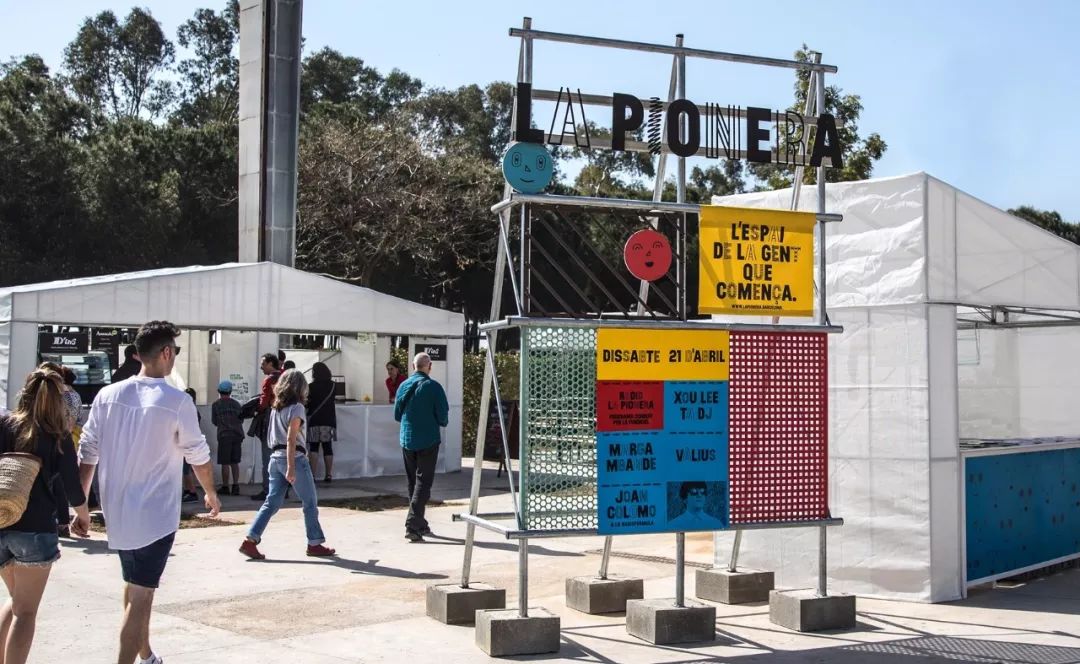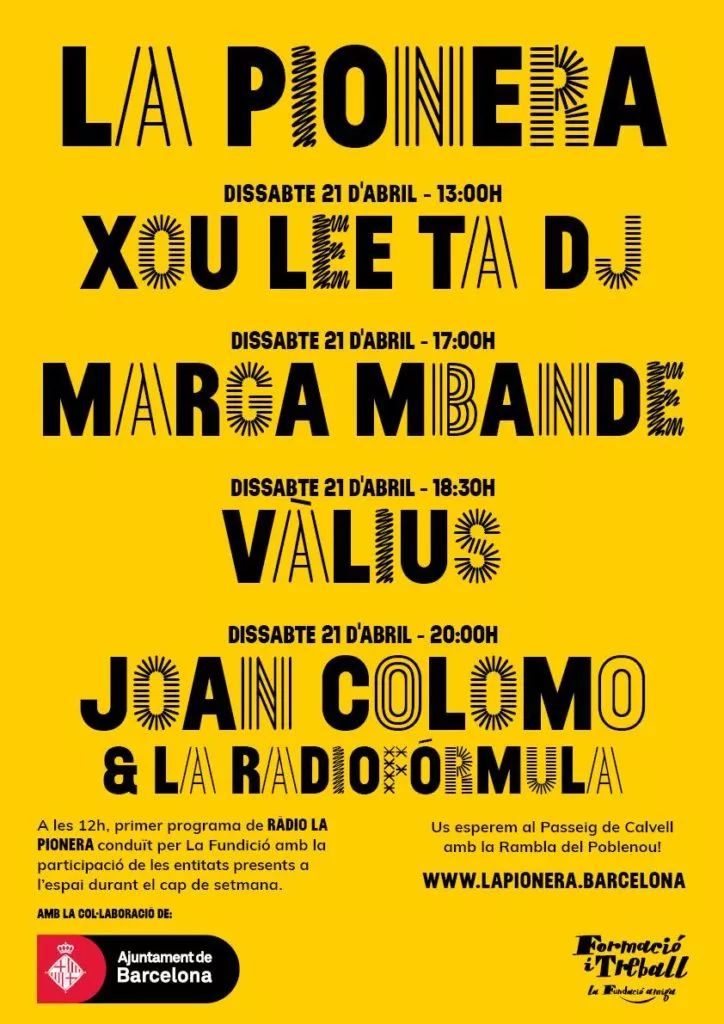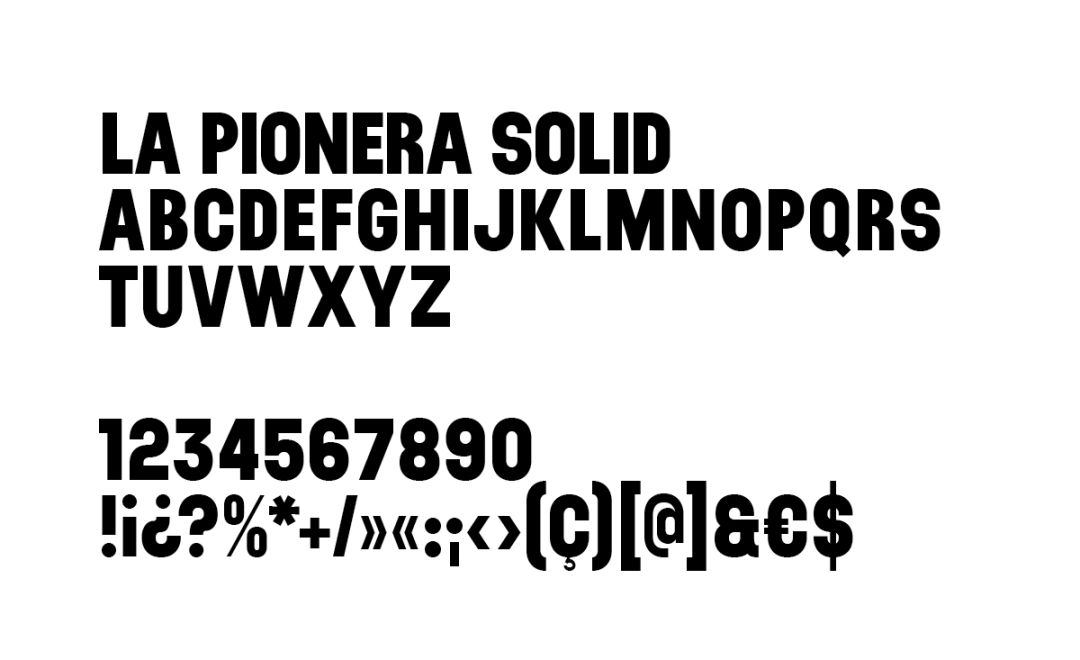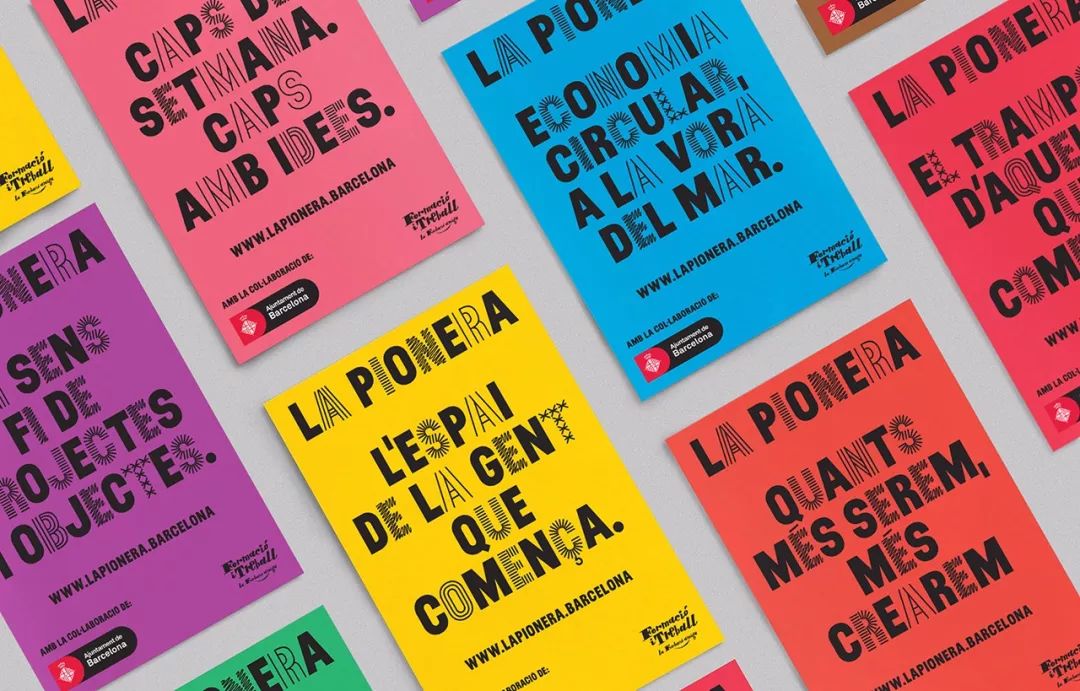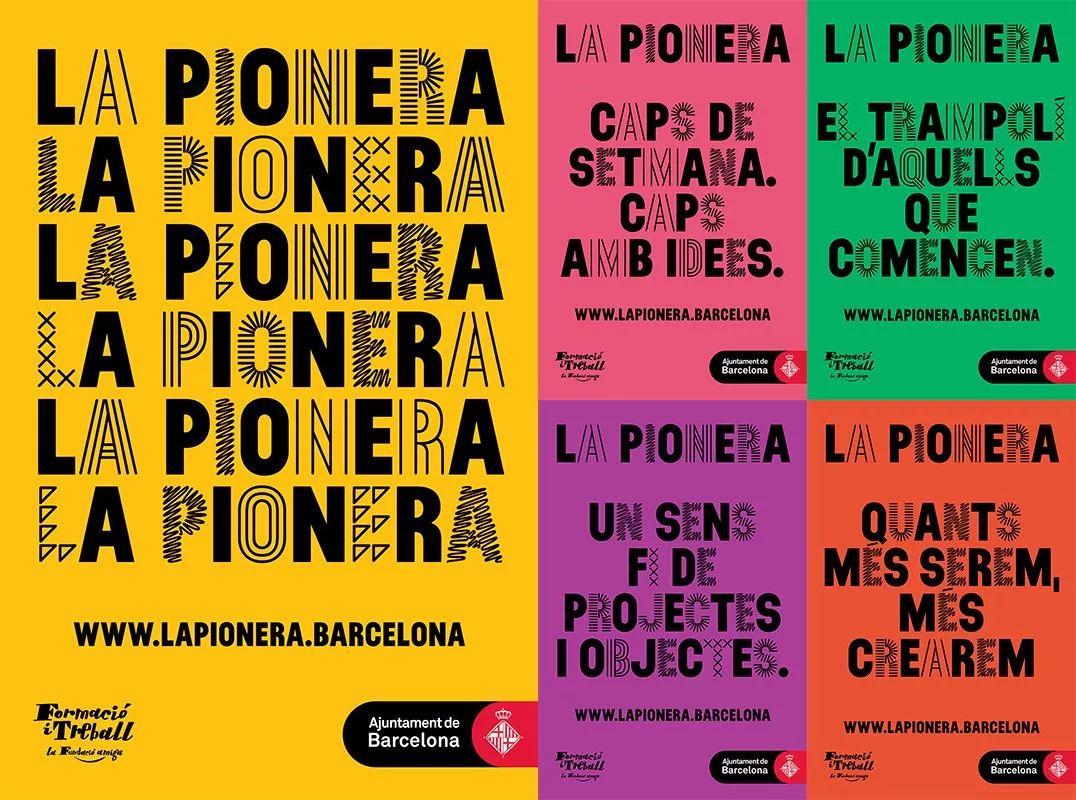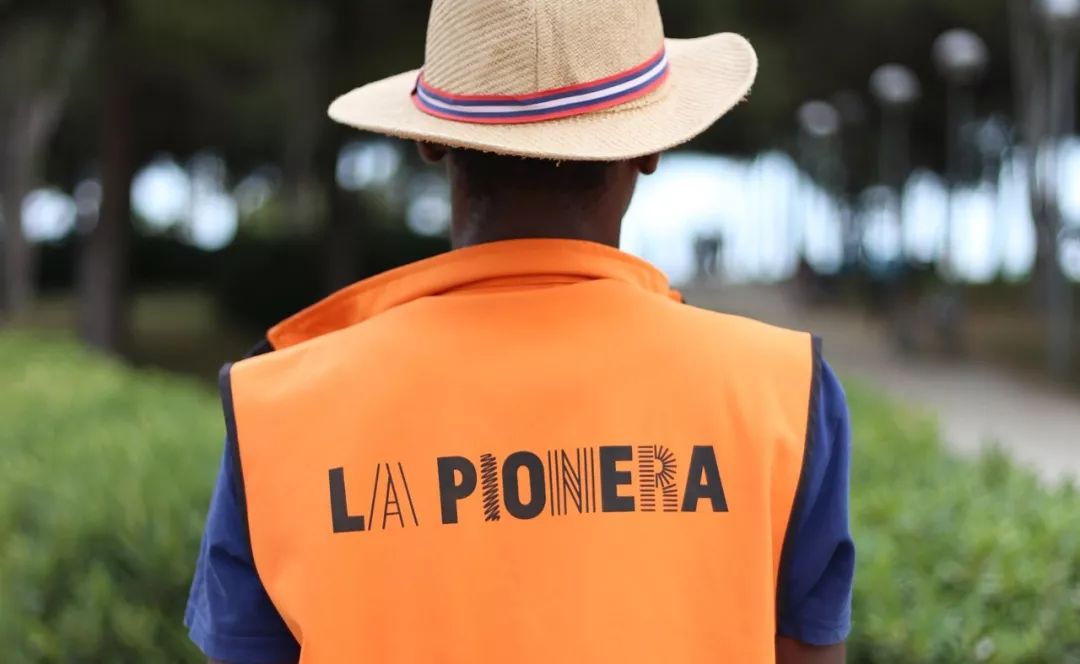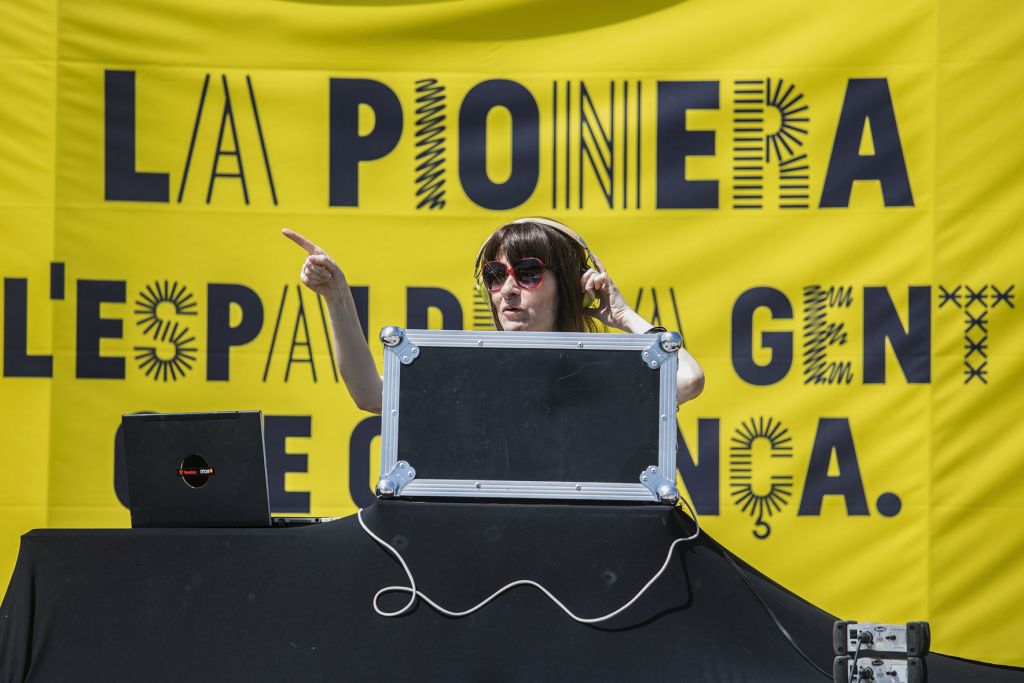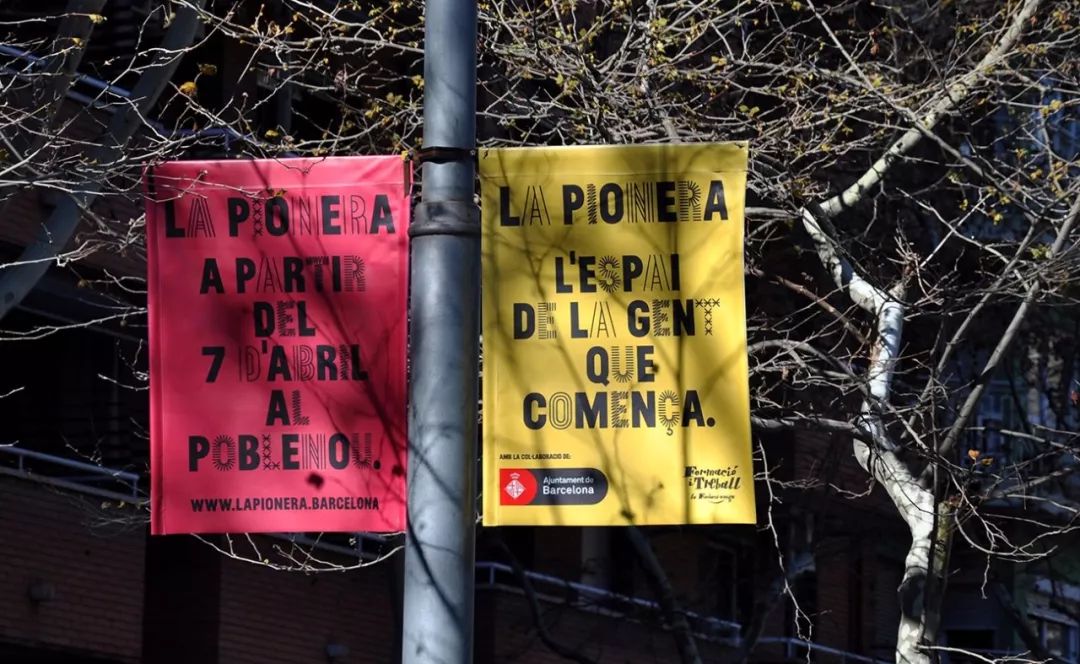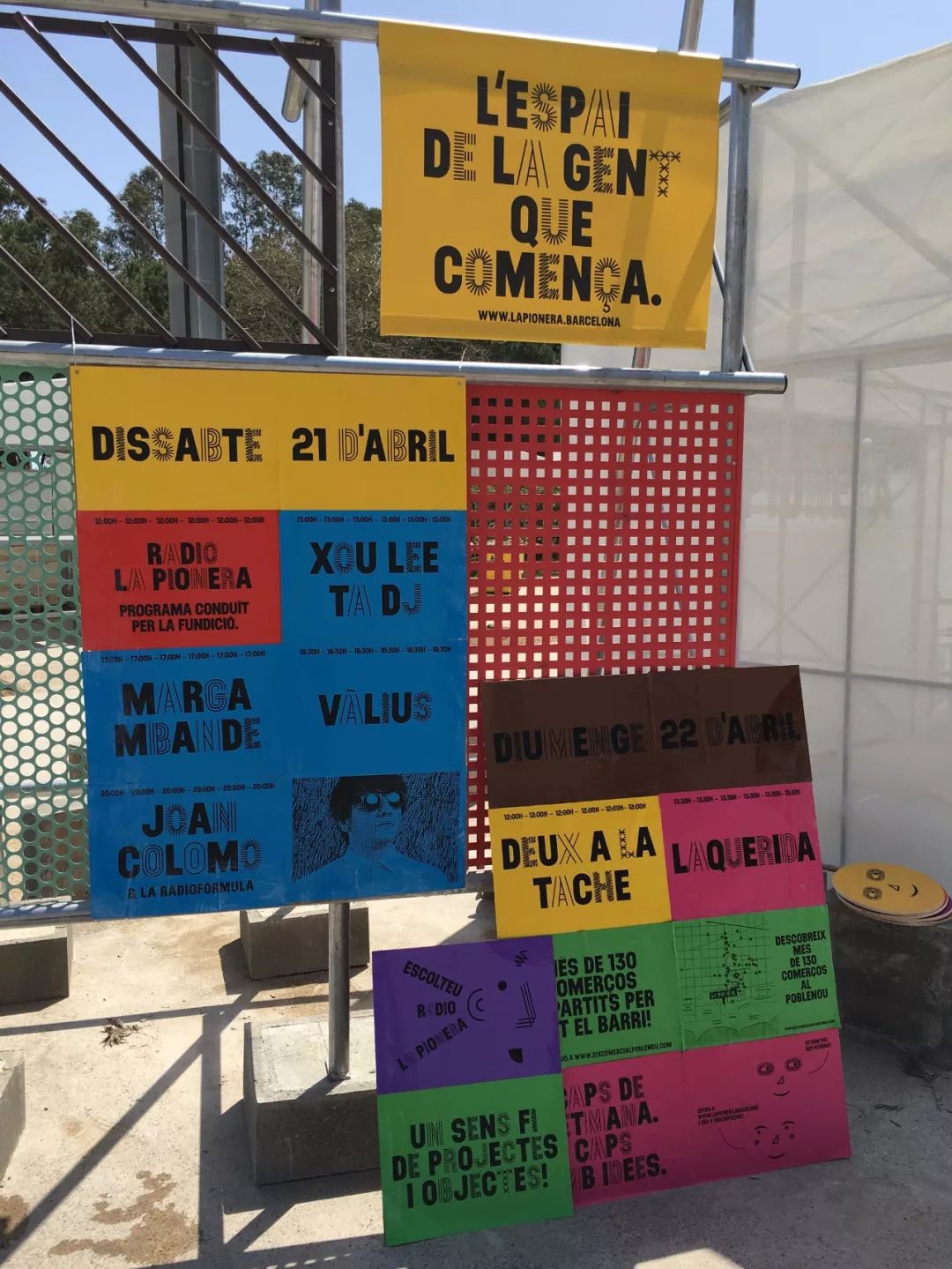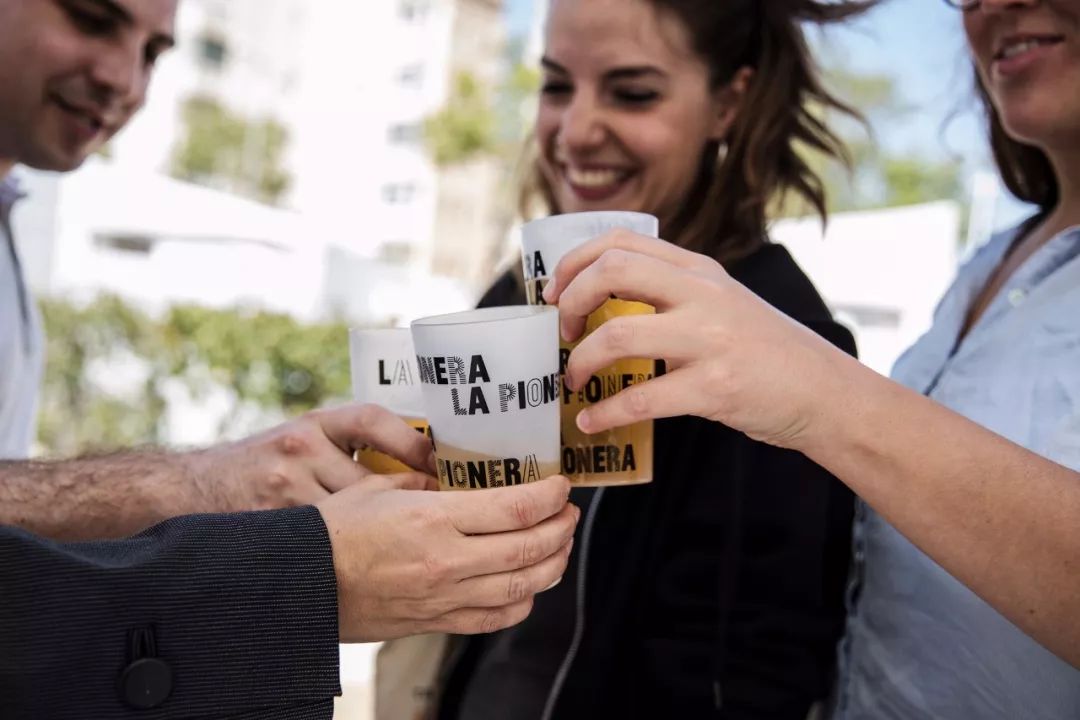
La Pionera是开设于2018新开设的一个露天空间,用以促进市民和项目之间的合作。
项目的LOGO是这样的。这个项目由巴塞罗那市(Ajuntament de Barcelona)推动,这是对于那些创业人士和专注于社会经济创新的新项目来说是一个很好的机会。
La Pionera项目由巴塞罗那市(Ajuntament de Barcelona)推动。这里每个月都会举办一次展览,预计在2018-19年间,这里将会有300多个不同的活动和项目。
来自巴塞罗那的131工作室设计了La Pionera的视觉形象。
以创业人员和项目的可样性作为切入点,131工作室设计了一套灵活的排版系统。
La Pionera的视觉系统围绕着26个实心字母和52个可自发替代相应字符的花体字符构建,实心字符和花体字符可以互换,以生成易于构建的扩展性语言。我们通过视频来了解一下——
这套视觉系统的妙处在于,它用新鲜和直白的语调,为La Pionera举办的各种活动,如音乐会、马戏团、舞蹈、演讲等,都能快速设计出生动的广告画面,而不会让人感觉枯燥乏味。
这个强大功能的背后,是一个程序员Santi Grau开发的应用程序。这套程序可以生成由互换字母组成的版面,并可以立即打印出来。这个程序无所不能,从街道海报、标识标牌,到La Pionera里涉及的所有内容,它都能应付自如。
与定制字体同一风格的表情符号,我们目前还没有看到这些符号的应用,估计后期会不断加入。
“La Pionera”在西班牙语里是先锋的意思,这个女性化的名字由Nom Nam提供。“先锋”意味着开天辟地,同样,La Pionera也是一个为他人提供更多机会的空间。
主办方举办了一项色彩鲜艳的活动,让巴塞罗那的市民们更好地了解这个项目。